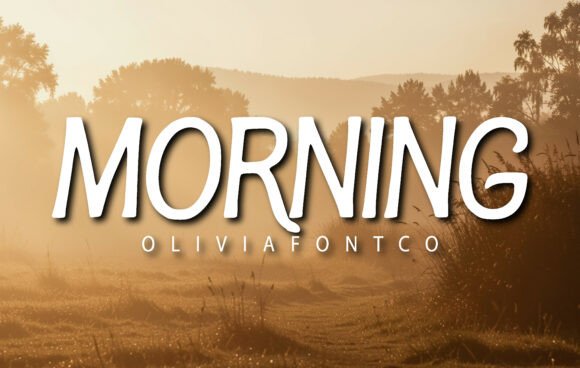
Morning
قد يكون العثور على عناصر التصميم المناسبة أمرًا صعبًا، ولكن Morning يقدم مجموعة استثنائية ترتقي بعملك على الفور.
تم تصميمه بدقة، ويوفر Morning متجهات نظيفة وطباعة سلسة وترخيصًا تجاريًا لراحة بالك.
سواء كنت تقوم بإنشاء منتجات الطباعة عند الطلب أو دعوات الزفاف أو رسومات وسائل التواصل الاجتماعي، فإن Morning هو الخيار المثالي.